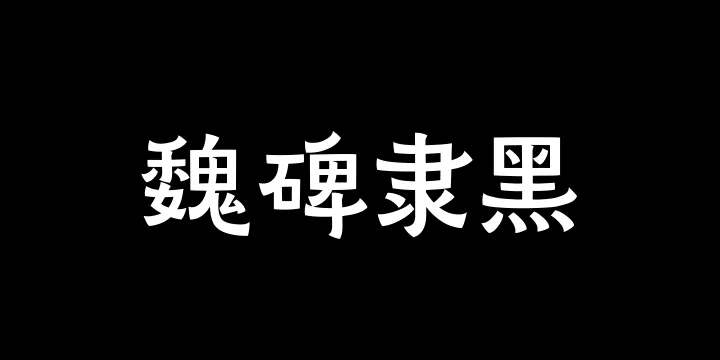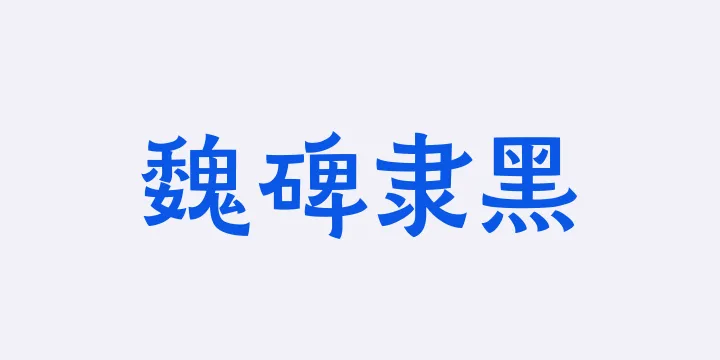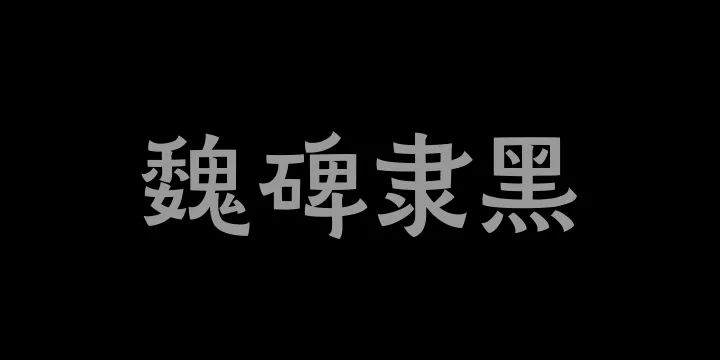
字体全名: 山海魏碑隶黑65W
字体简介: 山海魏碑隶黑65W,是一款全新隶书+黑体风格的字体,是山海魏碑隶黑字体家族系列中的常规粗细款,编号65W,包含汉字9169个,符号200+个。该字体是一款具有强劲视觉冲击力的隶书+黑体风格的字体。字形结构多为方形结构,如正方形、长方形或扁方形,强调字形的稳定性和内敛精神。字形大小悬殊,通过大小不一的字来形成对比和层次感,造型硬朗,直线与曲线结合的笔画构成棱角分明、坚实有力。